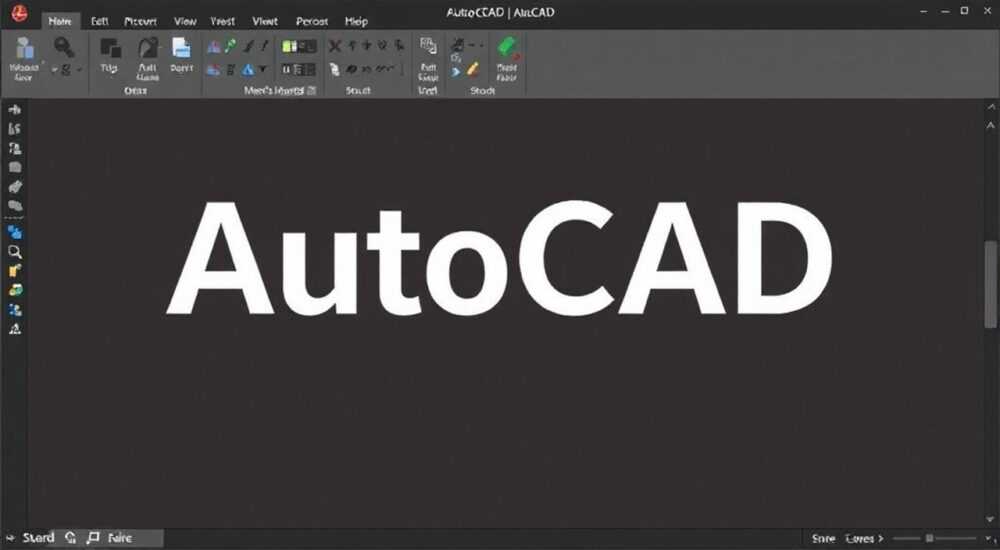
Как добавить шрифт в автокад
Добавление шрифтов в AutoCAD — важный процесс для обеспечения корректного отображения текста в чертежах, особенно при работе с нестандартными или специализированными стилями. Несоответствие шрифтов может привести к подмене символов, искажению надписей или потере читаемости при передаче файлов между пользователями. Решение этой задачи требует понимания структуры поиска шрифтов в AutoCAD, правильного размещения файлов и настройки текстовых стилей.
Автоматизированная система проектирования AutoCAD активно используется в архитектуре, машиностроении и строительстве, где точность оформления текстовой информации играет ключевую роль. Шрифты в AutoCAD делятся на два основных типа: TrueType (TTF) и собственные векторные (SHX). Каждый из них имеет свои особенности применения, требования к установке и поведение при обмене чертежами. Пользователи часто сталкиваются с проблемой «пропавших» шрифтов при открытии чужих DWG-файлов, что связано с отсутствием нужных файлов в локальной системе. Это делает знание процесса добавления шрифтов критически важным навыком.
Типы шрифтов в AutoCAD
AutoCAD поддерживает два основных формата шрифтов: TrueType (TTF) и Shape-шрифты (SHX). Их различие заключается в способе рендеринга, размере файла и степени контроля над отображением. TrueType — стандартный формат, используемый в операционной системе Windows. Он позволяет применять любые установленные в системе шрифты, такие как Arial, Times New Roman или Calibri. Эти шрифты легко читаются, масштабируются без потерь и поддерживают кириллицу и другие символы.
Shape-шрифты (SHX) — это компилированные векторные шрифты, созданные специально для AutoCAD. Они обеспечивают высокую скорость отрисовки, меньший размер чертежа и предсказуемое поведение при печати. Примеры включают ISOCP, TXT, COMPLEX и ISOCPEUR. SHX-шрифты часто используются в стандартизированных проектах, где требуется соответствие ГОСТ или ISO. Они не зависят от системы и всегда выглядят одинаково, независимо от того, на каком компьютере открыт чертёж.
Выбор между TTF и SHX зависит от задачи. Для внутренних заметок, аннотаций и презентаций подойдут TrueType. Для финальных чертежей, предназначенных к передаче заказчику или в производство, рекомендуются SHX — они минимизируют риски подмены шрифтов. При этом важно помнить, что SHX нельзя просто установить как системный шрифт — он должен быть доступен в путях поиска AutoCAD.
Преимущества и недостатки каждого типа
- TrueType (TTF): простота использования, богатая типографика, поддержка Unicode, но зависимость от системы и риск подмены при передаче файла.
- Shape-шрифты (SHX): стабильность, малый вес, контроль над начертанием, но ограниченный набор символов и необходимость ручной установки.
Критерий |
TrueType (TTF) |
Shape (SHX) |
Переносимость |
Низкая — зависит от ПК получателя |
Высокая — встроен в чертёж при наличии |
Поддержка кириллицы |
Зависит от шрифта |
Размер файла |
Больше |
Меньше |
Скорость отрисовки |
Медленнее |
Быстрее |
- В окне «Диспетчер текстовых стилей» нажмите «Новый», укажите имя стиля и выберите нужный шрифт из списка.
- Если шрифт не появился, перезапустите AutoCAD — программа кэширует список при запуске.
Для TrueType-шрифтов также можно использовать стандартную установку через Windows: кликнуть правой кнопкой по файлу .ttf и выбрать «Установить». После этого он станет доступен во всех приложениях, включая AutoCAD. Однако этот способ не гарантирует, что шрифт будет работать в старых версиях AutoCAD или на других компьютерах.
Настройка текстового стиля
После добавления файла необходимо привязать его к текстовому стилю. Стиль определяет не только шрифт, но и высоту, ширину, угол наклона и другие параметры. Если вы не зададите высоту в стиле (оставите 0), то при вставке текста сможете указывать её вручную. Если зададите значение — все надписи будут одной высоты.